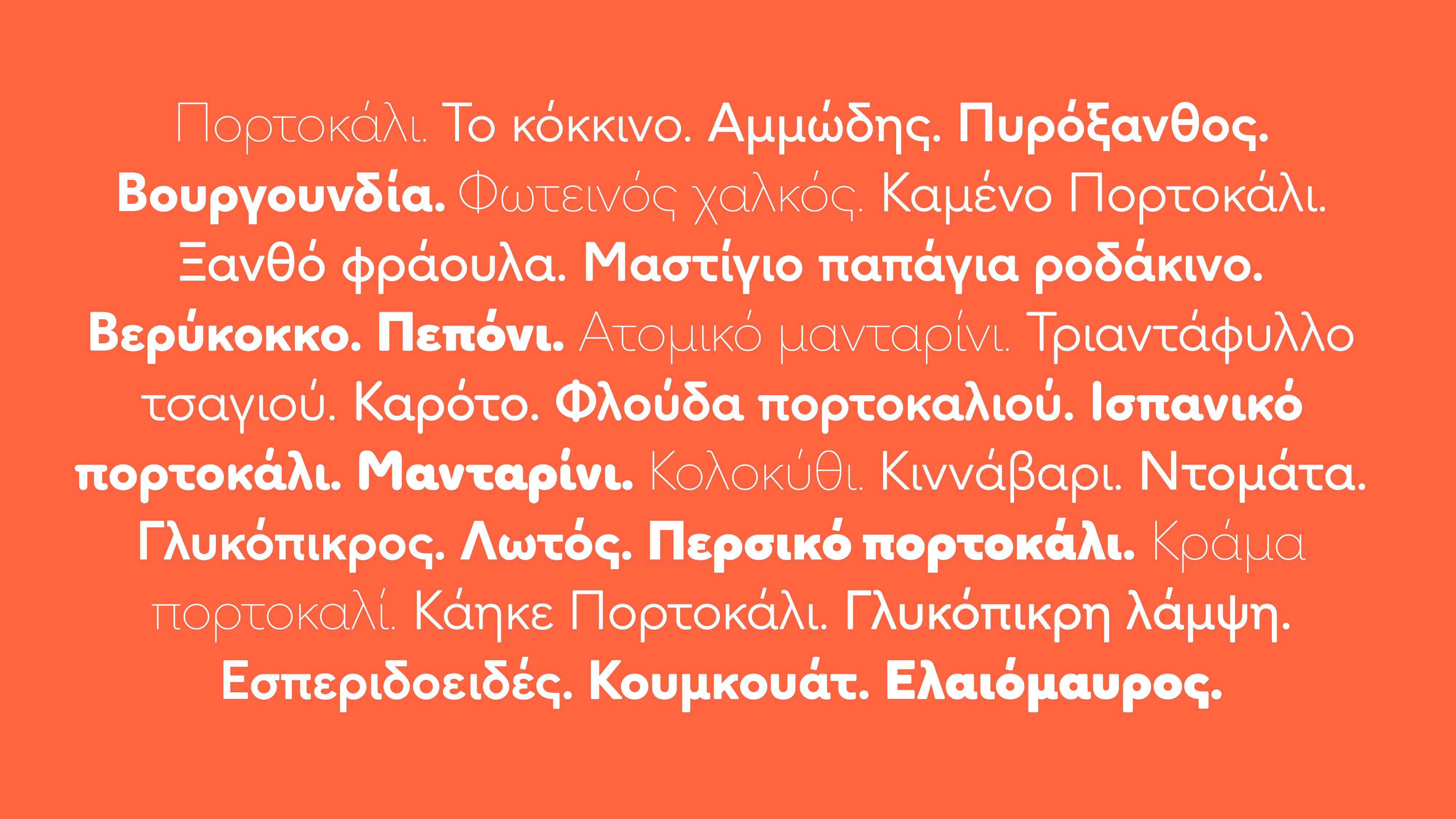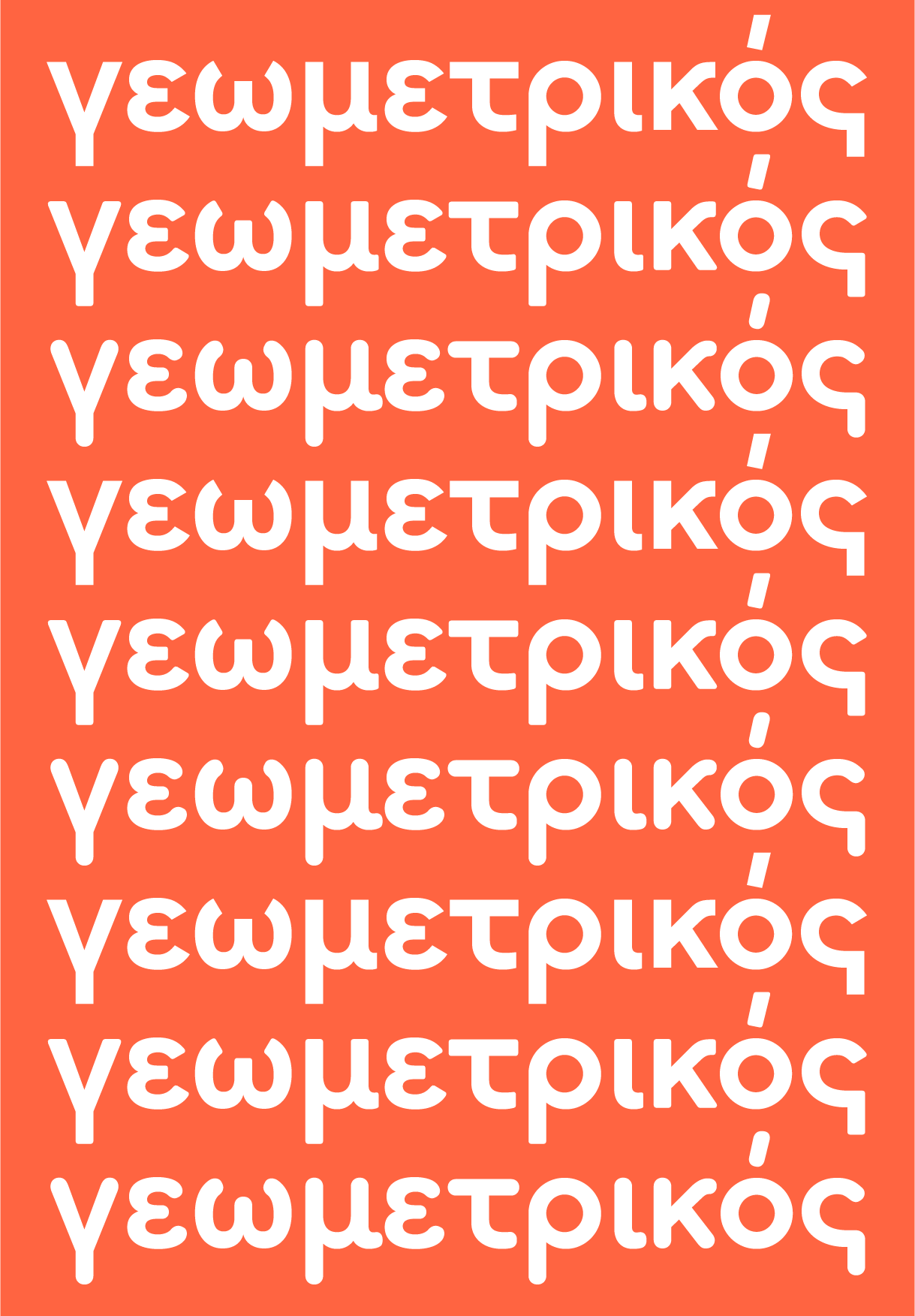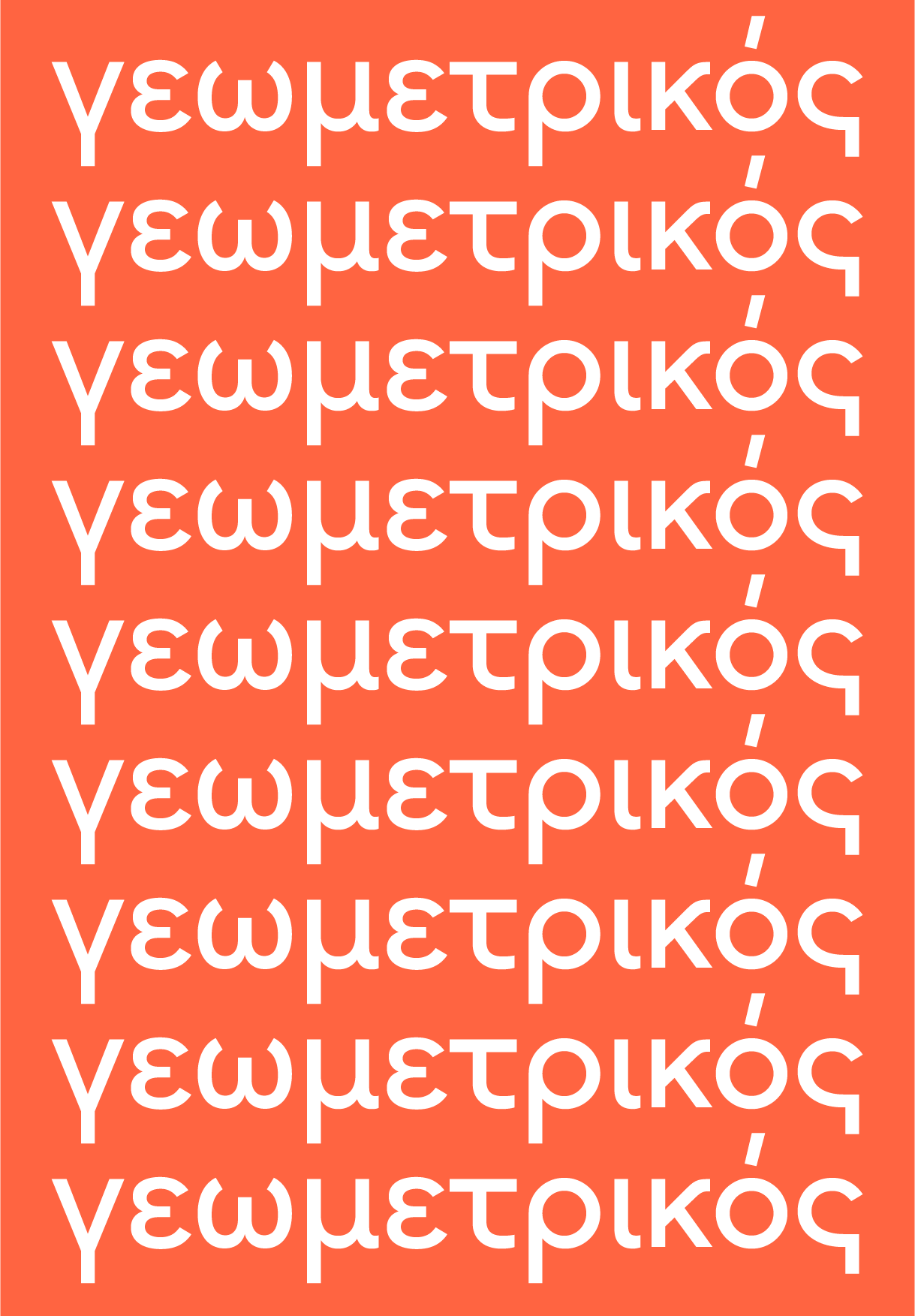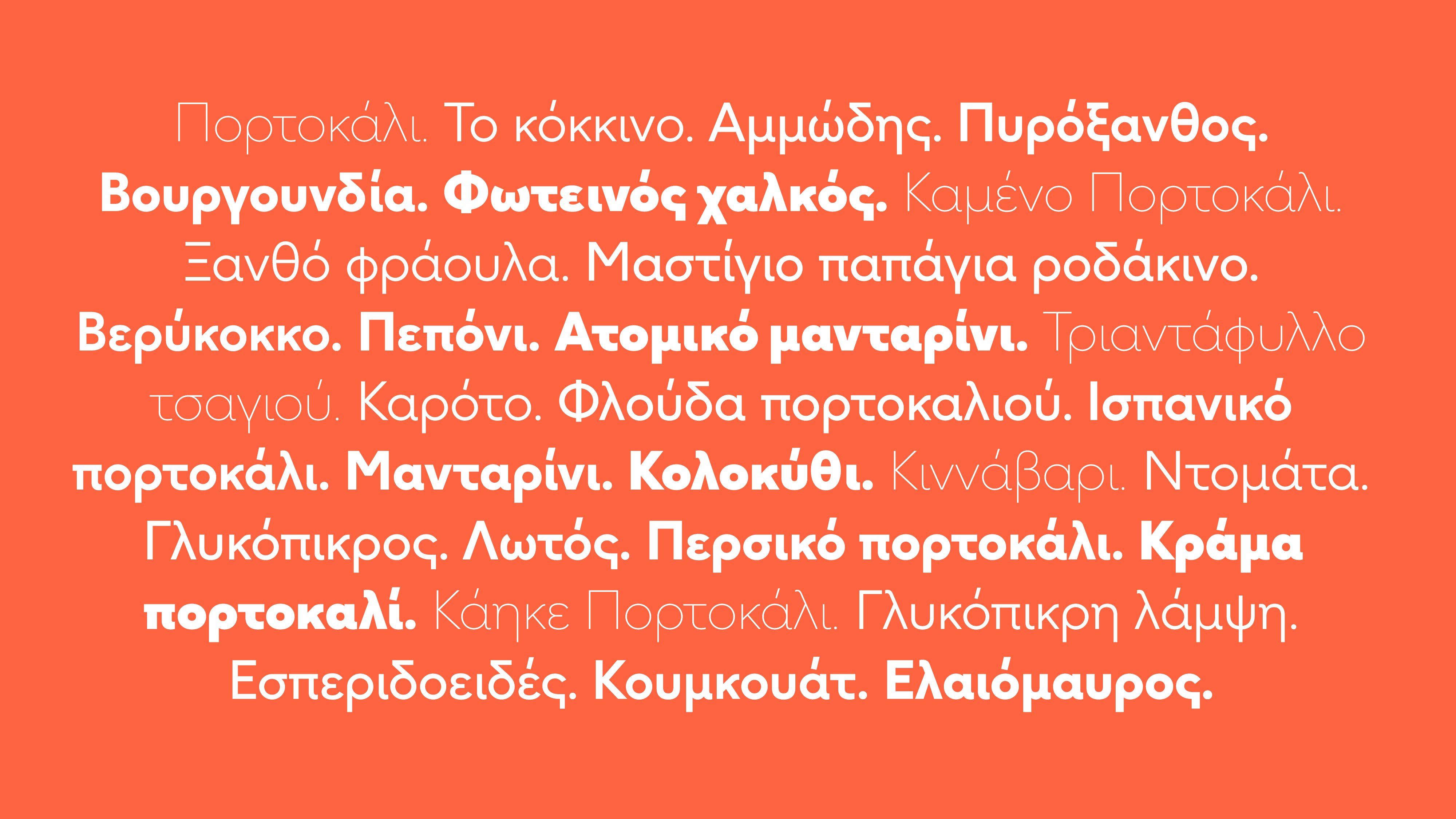
F37 Ginger Greek Font Sampler
Τα γεωμετρικά σχήματα F37 Ginger και οι ασυνήθιστοι σχεδόν κυκλικοί μετρητές, το καθιστούν ιδανική επιλογή για λογότυπα και τίτλους.
ΦΥΣΙΚΟΣ ΜΟΝΤΕΡΝΙΣΜΟΣ
Γεωμετρικός
→ Καθαρό και μοντέρνο ←
Κύκλοι, τετράγωνα και τρίγωνα